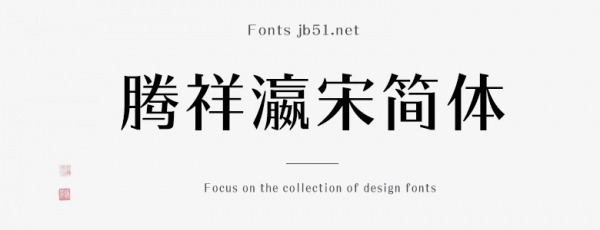
騰祥瀛宋簡體-W5是一款不錯的藝術(shù)字體,由騰祥字庫出品,這款字體筆觸適中,字形端正,適合應(yīng)用于藝術(shù)設(shè)計、平面宣傳設(shè)計、網(wǎng)頁設(shè)計,書法字帖等領(lǐng)域,需要的朋友可以前來本站下載。
此款字為騰祥瀛宋系列字庫,是騰祥公司自主精心設(shè)計開發(fā)的精品正文字庫。一共10款粗細,以期滿足用戶不同領(lǐng)域的用字需求。此款字為瀛宋W5,可用于正文、大小標題等。整個系列字庫風格完全一致,不管是常用字或是非常用字,字字精美、結(jié)構(gòu)端正、重心平穩(wěn)、美觀實用。此款字為騰祥公司推送《2019森澤字體大賽》參賽作品。